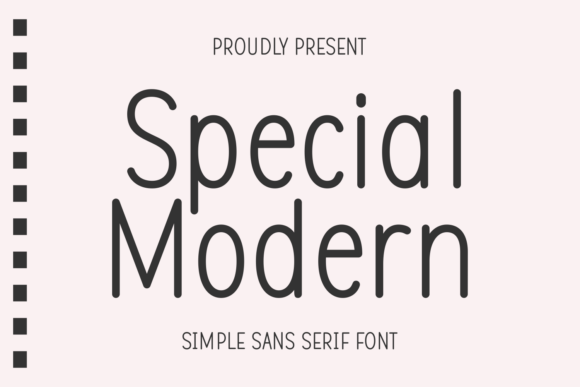
Special Modern
Special Modern – Revue détaillée d’une police sans‑serif ultra contemporaine
Vous cherchez une police qui allie minimalisme, lisibilité et modernité ? Special Modern répond parfaitement à ces exigences. Conçue comme une police sans‑serif simple, elle séduit par ses formes arrondies, ses proportions équilibrées et son charme épuré, idéal pour les projets de branding, le design éditorial, les visuels sur les réseaux sociaux et bien plus encore.
Les points forts de Special Modern
- Design épuré et arrondi : Les traits doux et les courbes subtiles offrent une impression amicale tout en restant professionnelle.
- Excellente lisibilité : Grâce à ses proportions harmonieuses, chaque caractère reste clair, même à petite taille.
- Polyvalence d’usage : Parfaite pour les logos, les titres de magazines, les posts Instagram, les présentations PowerPoint et les supports imprimés.
- Adaptabilité multilingue : Prise en charge complète des caractères latins, accentués et des glyphes européens.
Pourquoi choisir Special Modern pour vos projets ?
En choisissant Special Modern, vous misez sur une identité visuelle qui respire la confiance et la modernité. Sa présence subtile mais marquante renforce la reconnaissance de marque sans alourdir le design. De plus, son style minimaliste s’accorde facilement avec d’autres typographies, offrant ainsi une grande liberté créative.
Utilisations recommandées
- Logotypes et identité de marque
- Couvertures de magazines et mises en page éditoriales
- Publications sur les réseaux sociaux (Instagram, LinkedIn, Facebook)
- Infographies et présentations professionnelles
- Sites web et applications mobiles
Conclusion – La police qui donne du peps à vos créations
Special Modern se démarque comme une solution typographique moderne, lisible et élégante. Que vous soyez designer freelance, agence de communication ou créateur de contenu, cette police vous aidera à transmettre un message clair et contemporain. N’attendez plus pour intégrer Special Modern à votre boîte à outils et donner à vos projets le look moderne qu’ils méritent.